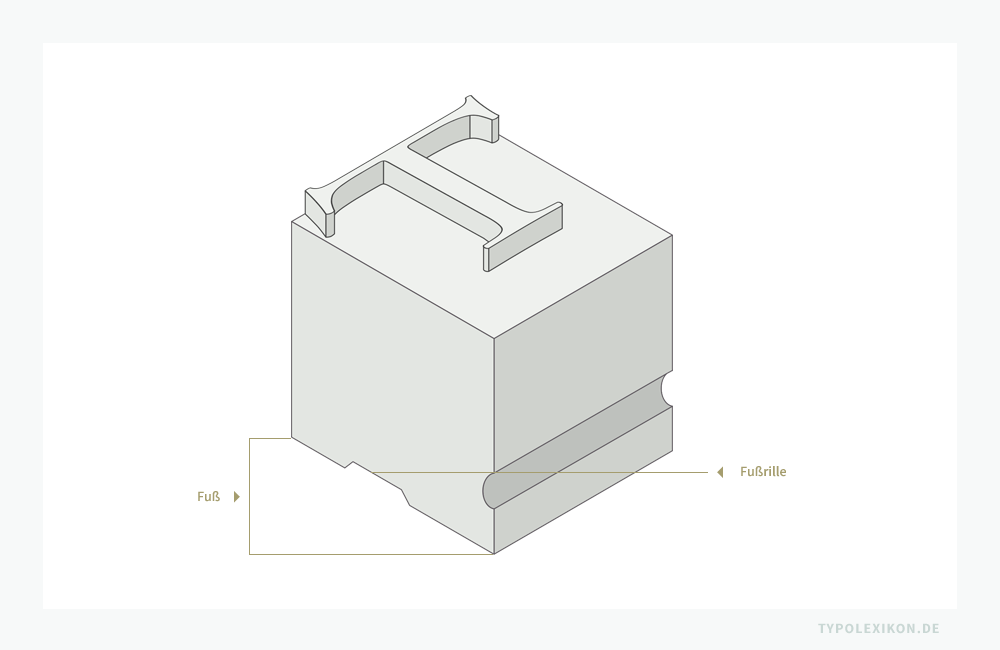
Fliegenkopf
Typografischer Fachausdruck aus dem gewerbespezifischen Sprachschatz dspr. Schriftsetzer, Schriftgießer und Drucker aus der Periode des materiellen Schriftsatzes mit physischen Drucktypen aus Metall (z.B. aus einer Blei-Zinn-Antimon-Kupfer-Legierung) für einen versehentlich oder absichtlich kopfüber, also verkehrt herum (ein)gesetzten Schriftkegel einer Drucktype; gedrehtes Blockadezeichen.
Der Begriff rührt daher, dass der verkehrt eingesetzte Schriftkegel im Druckbild des Andrucks (Korrekturabzug) ein oder zwei kleine Rechtecke ergibt, die vom Fuß (erhaben) und der Fußrille (nicht erhaben) des Kegels stammen und mit viel Phantasie und Humor einem »Fliegenkopf« ähnlich sehen.
Fuß und Fußrille (auch Anguß oder Gießrille) eines Schriftkegels einer physischen Drucktype aus Metall (z.B. aus einer Blei-Zinn-Antimon-Legierung) oder Holz (z.B. Plakatschrift).
Der Abdruck des »Fußes« eines Schriftkegels wird in der Typografie als »Fliegenkopf« bzw. als »Blockadezeichen« bzw. bei fehlerhafter Deblockade als »Zwiebelfisch« bezeichnet. Je nach Schriftguss kann er aus einem oder zwei Rechtecken bestehen, je nachdem, ob der Kegel eine Fußrille besitzt oder nicht. Im Beispiel links: Kegel ohne Fußrille mit einem rechteckiger Abdruck. Rechts: Kegel mit Fußrille mit einem Abdruck aus zwei Rechtecken.
Da im Werksatz kleiner Hochdruckereien nicht immer genügend Drucktypen einer Kegelgröße vorrätig sind, werden mit Fliegenköpfen auch fehlende Buchstaben im Stehsatz markiert, die dann nach der Fertigstellung der ersten Druckbögen durch die freigewordenen Lettern ausgetauscht werden.
Ist ein Schriftsatz mit Fliegenköpfen markiert, gilt dieser Stehsatz für den Druck als »blockiert«. 1)  Wird ein Fliegenkopf als gedrehtes Blockadezeichen bzw. als Konsultationszeichen für eine Korrektur oder einen Ersatzbuchstaben nach der Endkorrektur des Andrucks im Zuge der Deblockade nicht entfernt und deshalb irrtümlich im Auflagendruck gedruckt, spricht man in der Typografie von einem »Zwiebelfisch«.